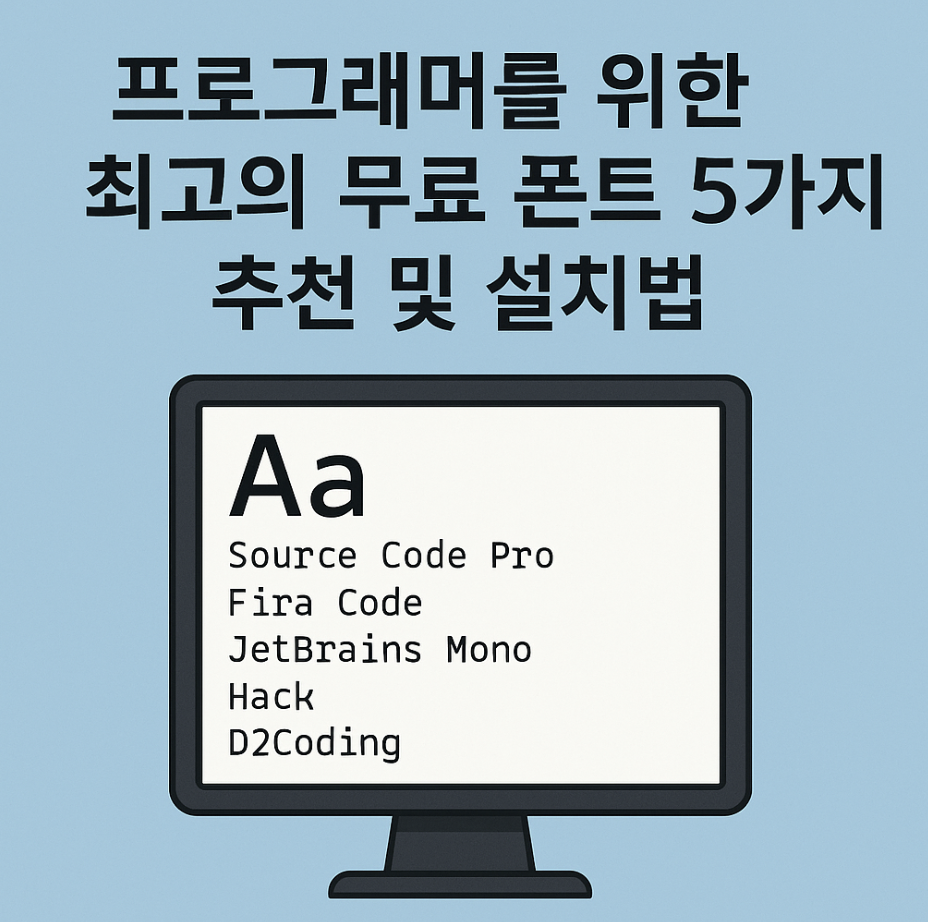
하루에도 수천, 수만 줄의 코드를 읽고 쓰는 프로그래머에게 '폰트'는 단순히 글자의 모양이 아닙니다. 장시간 코드를 봐도 눈이 편안해야 하고, 헷갈리기 쉬운 문자들을 명확하게 구분해 주어 버그를 줄여주는, 생산성과 직결되는 가장 중요한 '도구'입니다.
지금부터 전 세계 수많은 개발자들에게 사랑받으며, 여러분의 코딩 효율을 극대화해 줄 최고의 무료 코딩용 글꼴 5가지를 추천해 드립니다. 밋밋했던 코드 에디터 화면을 바꾸는 것만으로도, 코딩이 한결 즐거워지는 놀라운 경험을 하게 될 것입니다.
좋은 코딩 폰트, 무엇이 다른가요?
프로그래밍에 특화된 폰트는 일반적인 문서용 폰트와는 다른 몇 가지 중요한 특징을 가지고 있습니다. 첫째, 모든 글자의 가로 폭이 동일한 '고정폭(Monospaced)' 글꼴이어야 합니다. 이는 코드의 줄을 맞추고 전체적인 구조를 파악하는 데 필수적입니다.
둘째, 비슷하게 생긴 문자들을 명확하게 구분해 주어야 합니다. 예를 들어, 숫자 '0'과 알파벳 대문자 'O', 숫자 '1'과 알파벳 소문자 'l', 그리고 세미콜론(;)과 콜론(:) 등이 한눈에 구별되어야 어이없는 실수를 줄일 수 있습니다. 마지막으로, 여러 문자가 합쳐져 하나의 새로운 기호처럼 보이는 '합자(Ligature)' 기능을 지원하면, 코드의 가독성을 한층 더 높여줍니다.
1. 코딩 폰트의 표준, 'D2Coding'
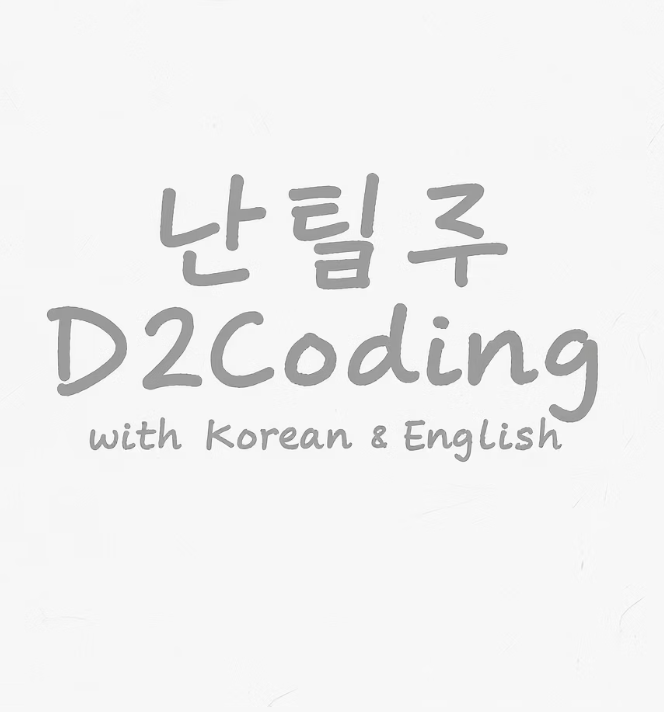
'D2Coding' 폰트는 네이버에서 개발하여 무료로 배포하는, 대한민국 개발자들을 위한 최고의 선물과도 같은 글꼴입니다. 영문은 물론 한글 환경에서도 최적의 가독성을 보여주며, 앞서 말한 좋은 코딩 폰트의 모든 조건을 완벽하게 만족시킵니다.
특히 한글과 영문을 섞어 쓸 때 이질감 없이 자연스럽게 어우러지고, '굵은 글씨(Bold)' 처리 시에도 뭉개짐 없이 선명하게 표현되는 것이 큰 장점입니다. 헷갈리기 쉬운 문자들이 명확하게 구분되도록 세심하게 디자인되어 있어, 코딩 입문자부터 숙련된 개발자까지 누구에게나 가장 먼저 추천하는 '국민 코딩 폰트'입니다.
2. 마이크로소프트의 역작, 'Cascadia Code'
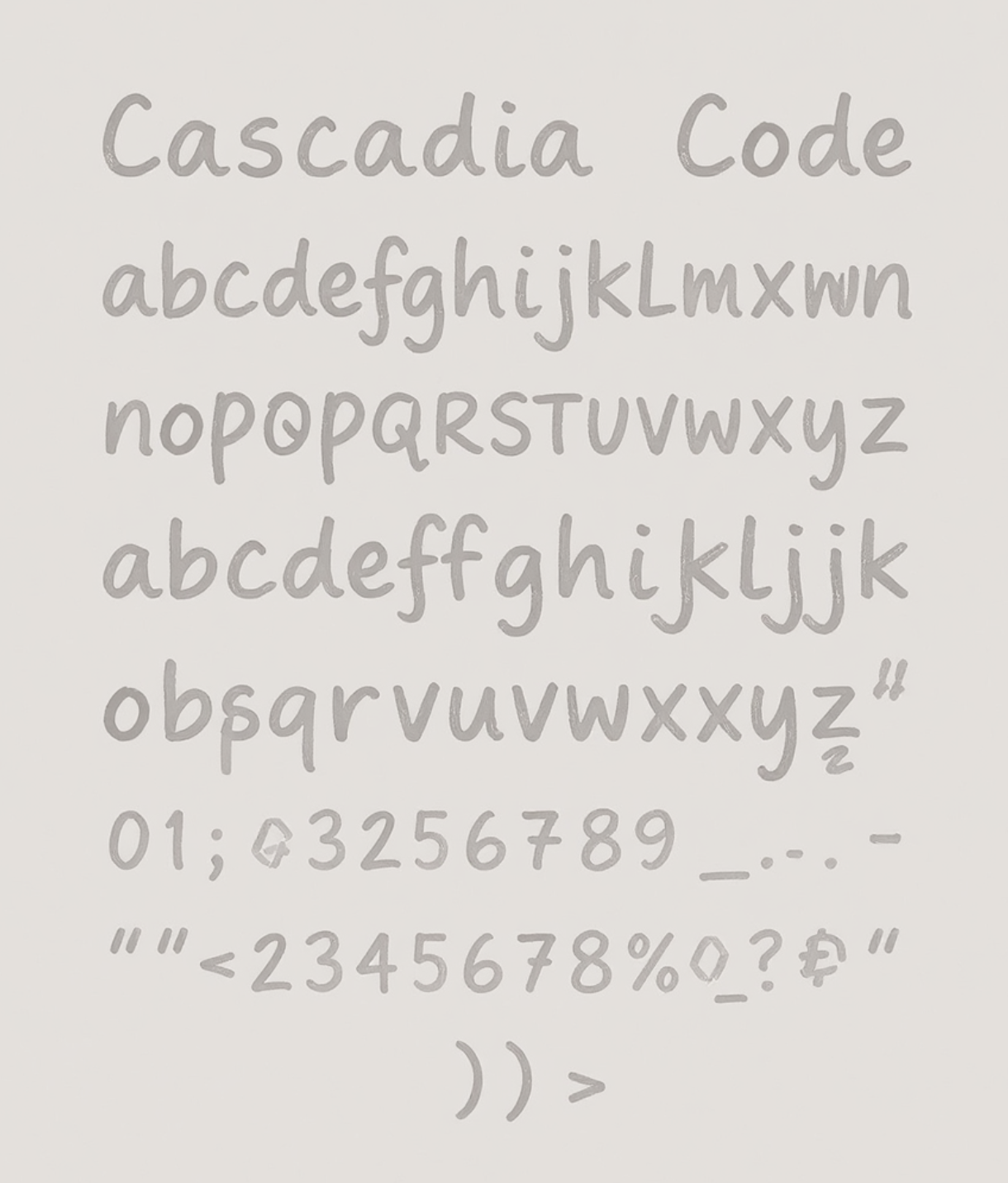
'Cascadia Code'는 마이크로소프트가 윈도우 터미널과 비주얼 스튜디오 코드를 위해 직접 개발한 최신 코딩용 글꼴입니다. 현대적인 디자인 감각과 뛰어난 가독성으로 전 세계 개발자들에게 빠르게 퍼져나가고 있습니다.
이 폰트의 가장 큰 특징은 화살표(->)나 비교 연산자(>=) 같은 여러 기호를 입력하면, 마치 하나의 새로운 그림문자처럼 자연스럽게 합쳐서 보여주는 '합자(Ligature)' 기능을 기본으로 지원한다는 점입니다. 이 기능은 코드를 훨씬 더 깔끔하고 직관적으로 보이게 만들어, 코드를 읽는 즐거움을 더해주는 확실한 해결책이 됩니다.
3. IBM이 만든 명품, 'Plex Mono'
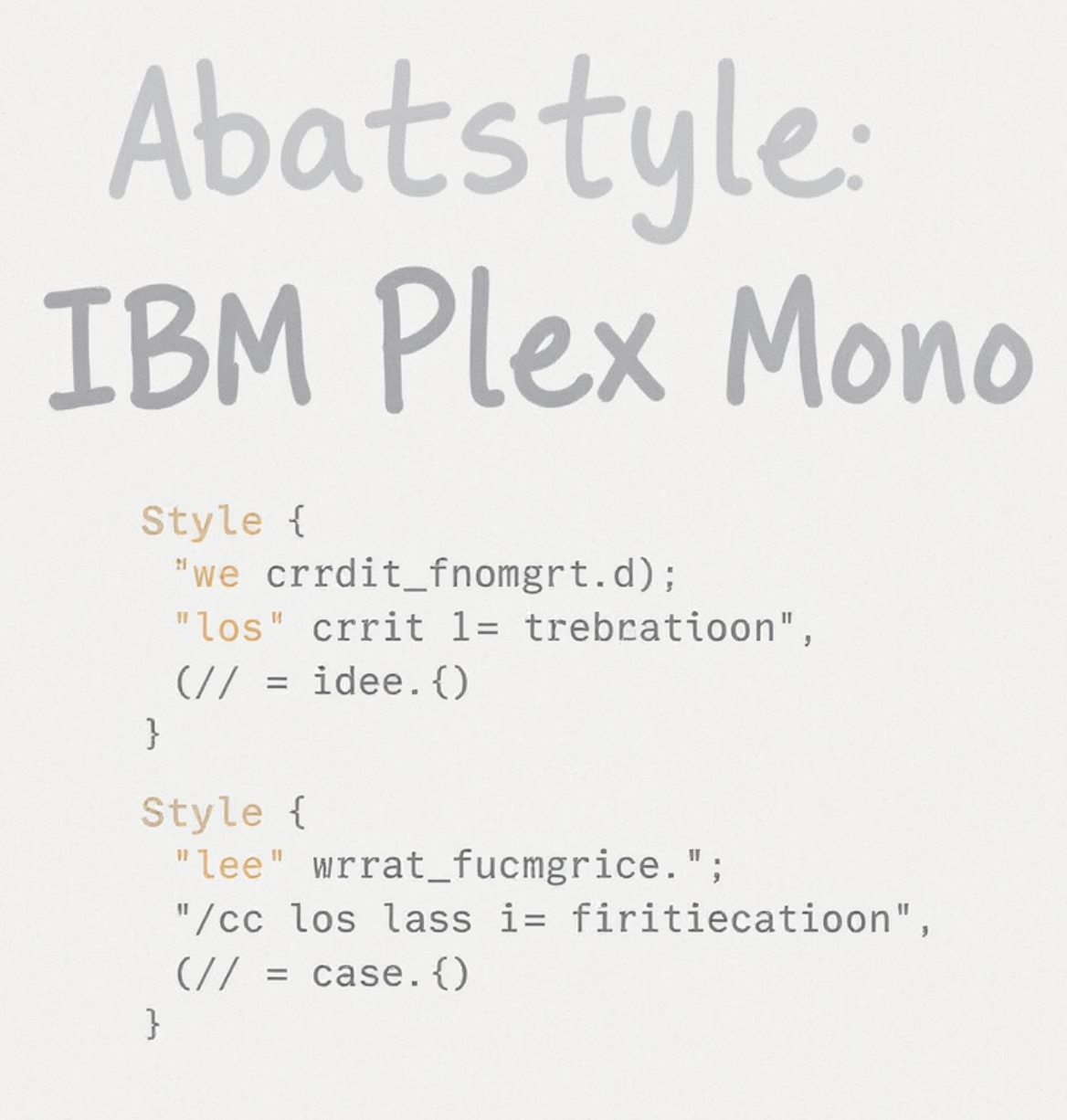
'IBM Plex Mono'는 세계적인 기업 IBM이 자사의 디자인 철학을 담아 만든 무료 폰트 시리즈 중 하나입니다. 공학적인 정교함과 세련된 디자인이 돋보이며, 특히 이탤릭체(기울임꼴)가 매우 아름답게 디자인되어 코드의 주석이나 특정 부분을 강조할 때 시각적인 만족감을 줍니다.
다른 코딩 폰트들에 비해 살짝 부드러운 인상을 주면서도, 각 문자의 형태가 명확하여 오랜 시간 화면을 봐도 눈이 편안합니다. 남들과는 다른, 조금 더 특별하고 감각적인 코딩 환경을 꾸미고 싶은 개발자에게 강력하게 추천하는 글꼴입니다.
4. 개발자의, 개발자를 위한, 'Fira Code'
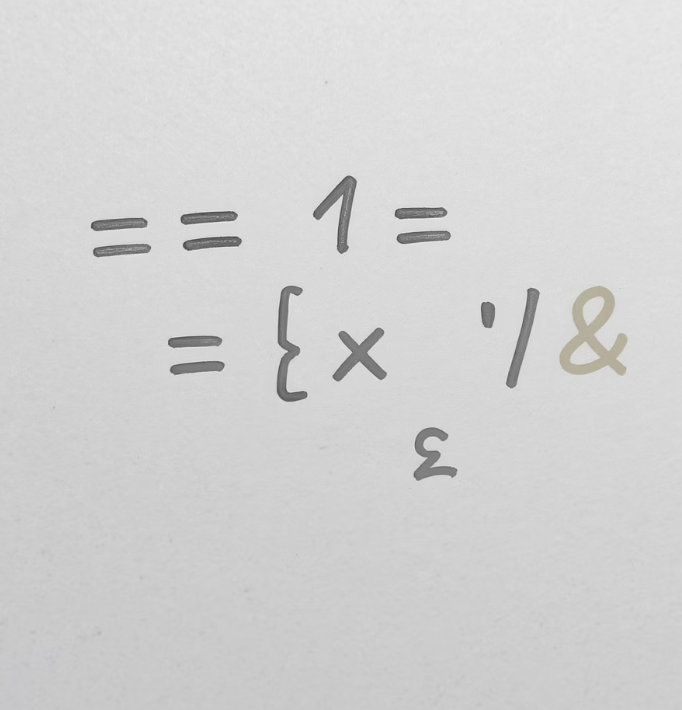
'Fira Code'는 앞서 소개한 Cascadia Code처럼 '합자(Ligature)' 기능을 적극적으로 활용하여 코드의 가독성을 극대화하는 데 초점을 맞춘 폰트입니다. 프로그래머들이 자주 사용하는 다양한 연산자와 기호 조합을 아름다운 합자 형태로 표현해 주어, 마치 잘 디자인된 수학 공식처럼 코드를 볼 수 있게 해줍니다.
'같지 않다(!=)' 기호가 수학의 '≠' 모양으로 변하는 등, 코드의 의미를 시각적으로 더 명확하게 전달해 주는 것이 특징입니다. 이러한 합자 기능에 매력을 느끼는 개발자들에게는 그 어떤 폰트보다 최고의 선택지가 될 것입니다.
5. 구글이 선택한 가독성, 'Source Code Pro'
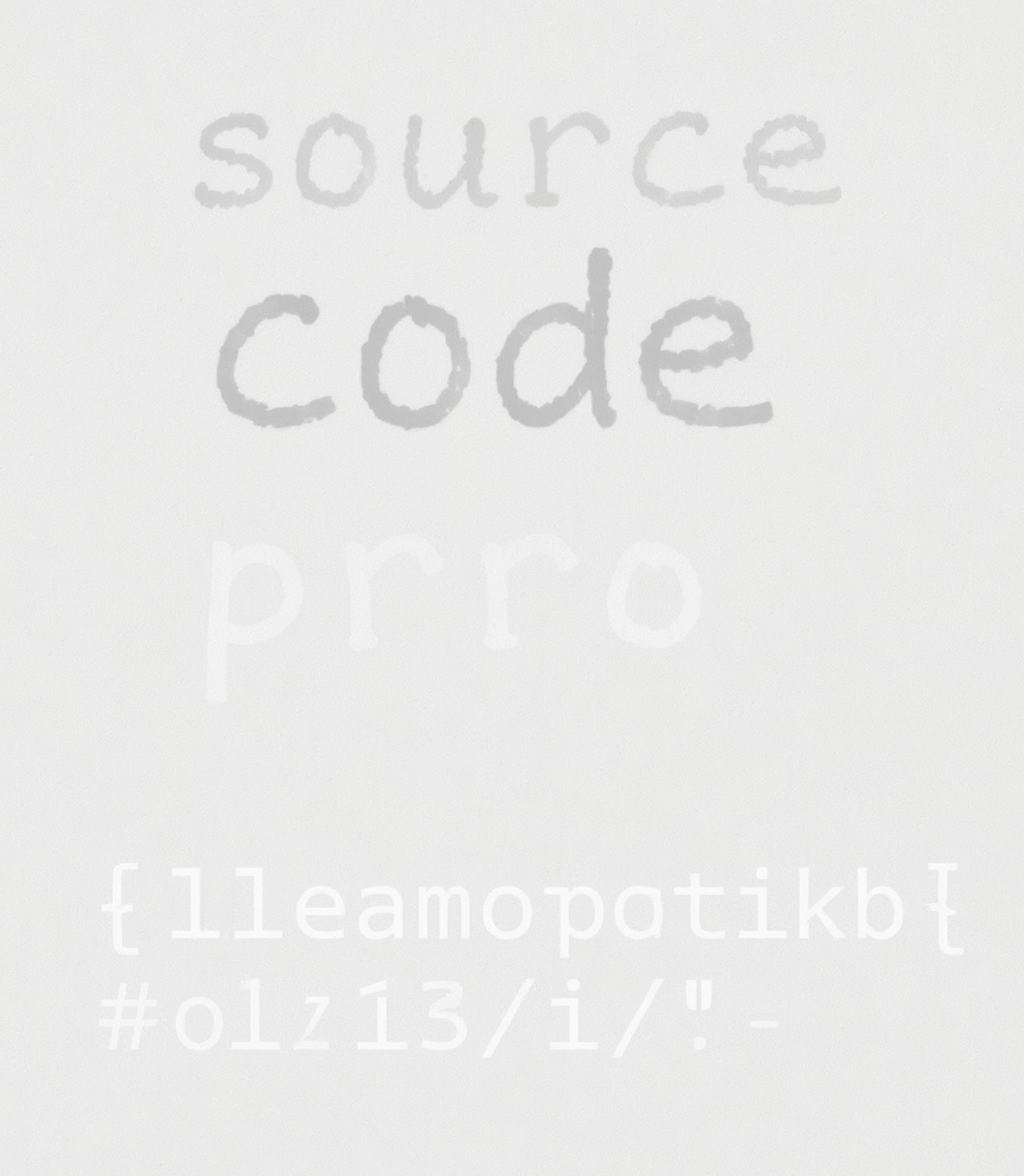
'Source Code Pro'는 어도비(Adobe)가 개발하고 구글이 웹 폰트로 선택하여 널리 알려진, 신뢰도 높은 오픈소스 코딩 폰트입니다. 군더더기 없이 깔끔하고 담백한 디자인으로, 어떤 환경에서나 무난하게 잘 어울리는 것이 가장 큰 장점입니다.
특별히 튀는 개성은 없지만, 가장 기본적인 '가독성'이라는 본질에 충실하게 디자인되었습니다. 오랜 시간 검증받은 안정감과 편안함을 선호하는 개발자라면, Source Code Pro는 결코 후회하지 않을 선택이 될 것입니다.